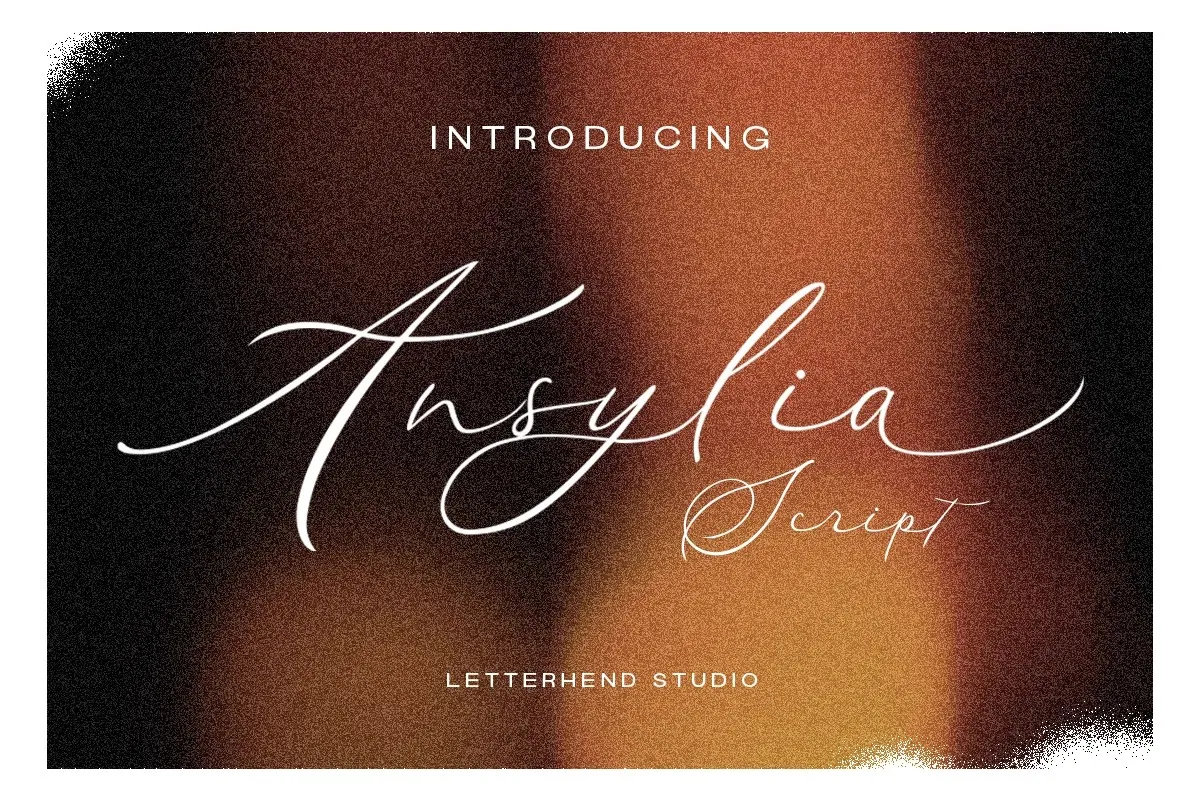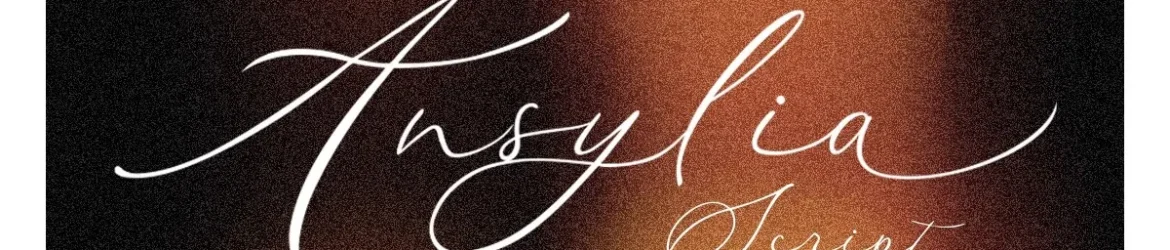
A Ansylia Font é uma nova tipografia de script criada pelo Letterhend Studio com um alinhamento não regular da linha base. Esta fonte carrega um estilo trendy e feminino, perfeitamente projetada para ser aplicada tanto em logotipos quanto em outros formatos formais como convites, etiquetas, logos, magazines, livros, cartas de cumprimentos ou casamentos, embalagens, moda, maquiagem, material escolar, novelas e até mesmo materiais de propaganda. Em um mundo onde a criatividade é valorizada, a Ansylia Font oferece uma opção elegante e moderna para seus projetos. Seja para criar um logotipo memorável ou adicionar um toque sofisticado ao seu design gráfico, esta fonte pode ser sua melhor aliada.